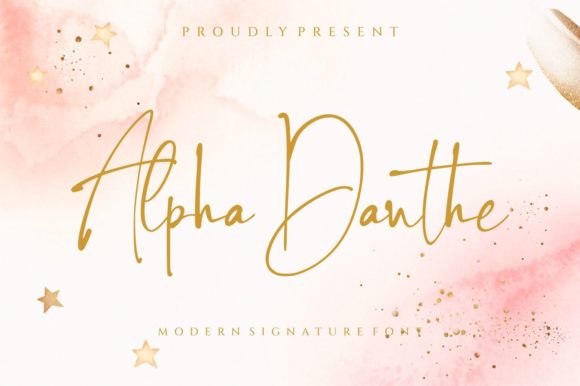
Alpha Danthe - шикарный, изысканный шрифт, излучающий утонченность и элегантность.
Стильные чередования и лигатуры делают этот шрифт идеальным для любого проекта.